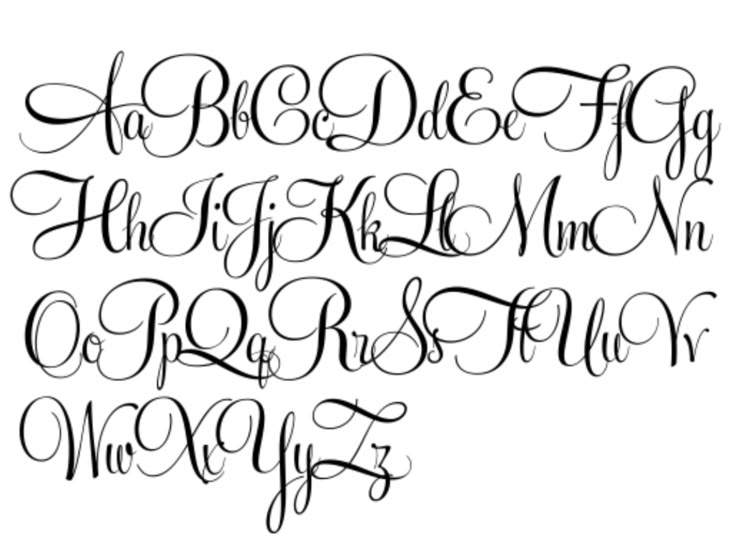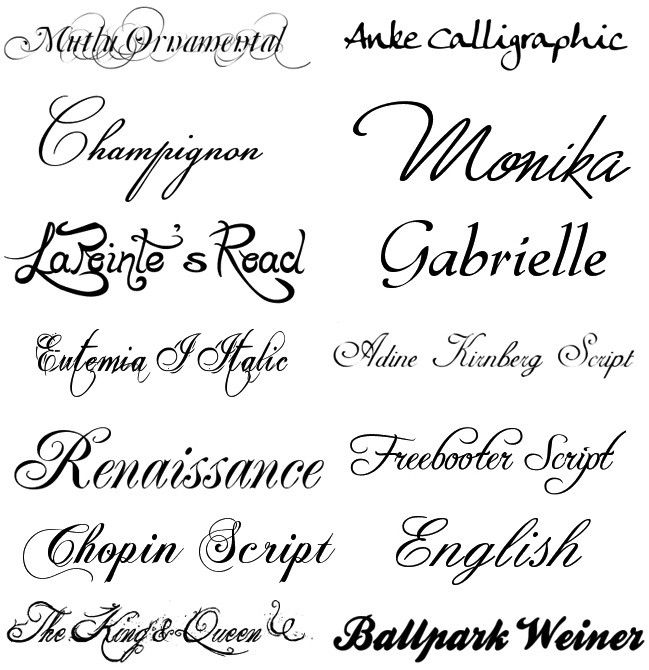
Татуировки были популярны всегда. В древние времена они несли информацию о своем обладателе, его статусе и положении в обществе. Сегодня уже никто не судит о людях по надписям на их теле. Татуировки надписи стали еще одним способом самовыражения, который использует не только молодежь, но и люди постарше.
В качестве тату, что только не используют, разнообразные рисунки, абстракции и вязи непонятных символов, но особой любовью у молодежи пользуются тату надписи. Это наиболее яркий способ выразить себя, сказать миру и окружающим людям, о своих мыслях и предпочтениях, донести свой взгляд на вещи.
Татуировки все также многое говорят о своем обладателе. Но теперь уже – это информация о том, какого стиля жизни он придерживается, каким характером обладает.
Все чаще молодежь выбирает латинский шрифт для тату. Это современно и модно, стильно и ярко. Да, и что говорить, ассортимент латинских шрифтов гораздо более широк, чем тех же русских.
Сегодня, когда в моде все иностранное – одежда, музыка, книги, неудивительно, что выбор подрастающего поколения падает именно на латинский шрифт для татуировок.
Этот важный вопрос предстоит решить перед тем, кто решил сделать татуировку, ведь хочется, чтобы надпись не только «говорила» о внутреннем мире, но и выглядела стильно и оригинально. У нас на сайте представлены все существующие шрифты для татуировок на латыни, начиная от древних и заканчивая современными. Готический шрифт или эмо, плавные линии и резкие углы, витиеватая вязь или строгие печатные буквы – найдется всё.
Тестовые татуировки на сегодняшний день пользуются огромной популярностью и являются наиболее востребованным направлением в нательном рисунке. Особенно ими увлекаются молодые люди, которым важно не только быть в тренде, но и заявить окружающему миру о своей уникальности и значимости.
И девушки, и парни испытывают особый интерес к изречениям, известным или не очень, на философские тематики, а также вечную любовную тему.
В большинстве случаев для татуировки выбирают текст на английском языке или на латыни, хотя некоторые ищут шрифты для тату, используя онлайн подбор на русском языке.
От чего зависит уникальность татуировки?
Чтобы украсить себя красивой и оригинальной татуировкой, нанесенной на плечо, запястье или щиколотку, важно не только найти высказывание, которое наилучшим образом передает вашу сущность и ваши личные убеждения, но и выбрать подходящий шрифт.
Качество надписи и ее внешний вид во многом зависит от удачного шрифта, поэтому не стоит пускать это дело на самотек, а лучше воспользоваться такой услугой, как.
Как выбрать «свой» шрифт?
К вопросу выбора шрифта стоит отнестись ответственно, поскольку именно от него зависит, насколько эффектно и уместно будет смотреться надпись, будет ли она привлекать взгляды окружающих или вызывать плохо скрываемое недоумение. Все шрифты для тату (онлайн подбор бесплатно ) обладают неповторимыми формами и своим размером.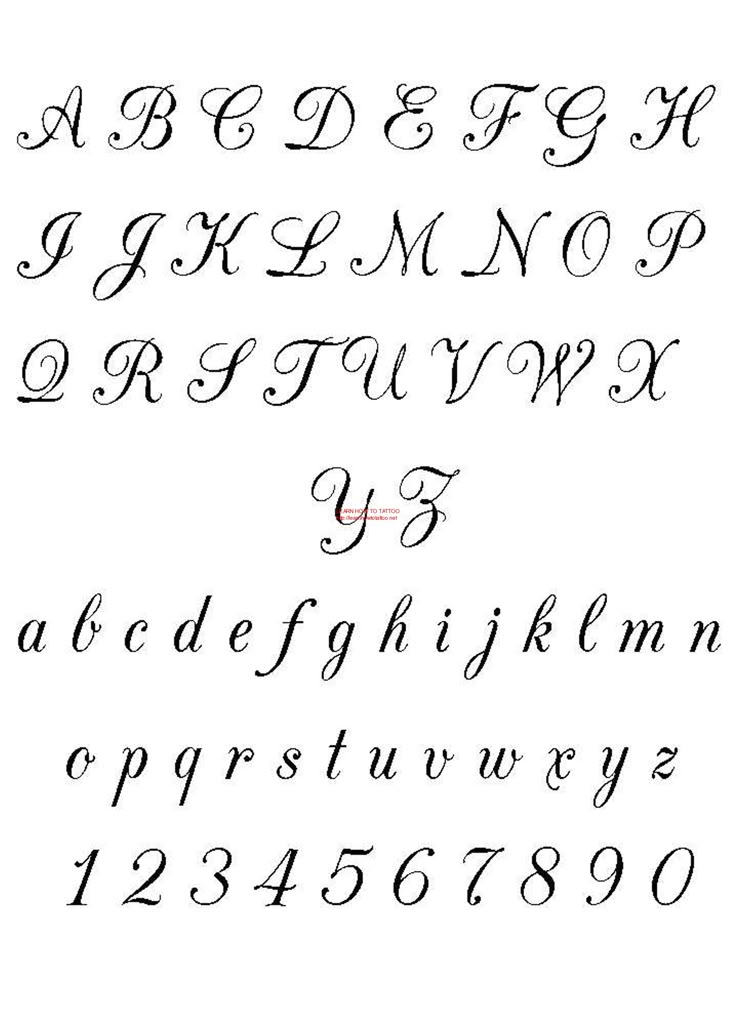
Как выбрать «свой» шрифт?
Нанесение татуировки – решение серьезное, ведь подразумевается, что вы будете носить ее до конца жизни, поэтому не стоит спешить, и прежде чем отправляться в тату-салон, стоит провести немного времени за компьютером и найти то, что вам понравиться. Чтобы надпись удалась, следует вбить в поисковик простую фразу: и интернет выдаст вам сотни вариантов, один из которых вам особенно придется по душе, и будет соответствовать вашему стилю.
Чтобы мастер мог создать тату надпись так, чтобы вы не пожалели о том, что выбрали, принять правильное решение бывает весьма непросто. Тем боле, что татуировка является подтверждением вашей индивидуальности, а значит и стиль, в котором будет выполнена надпись, должен быть особенным.
Древние шрифты для татуировок на теле
Но как бы тяжело это не показалось на первый взгляд, нет ничего невозможного для того, кто задастся целью.
Поэтому нужно рассмотреть все возможные варианты, оценить каждый, взвесив преимущества и недостатки. Кроме того, следует самому себе дать ответ на один простой вопрос: что именно вы хотите видеть на себе и готовы ли вы смотреть на это каждый день?
Если вы сильно боитесь ошибиться, то подобные шрифты являются беспроигрышными и универсальными.